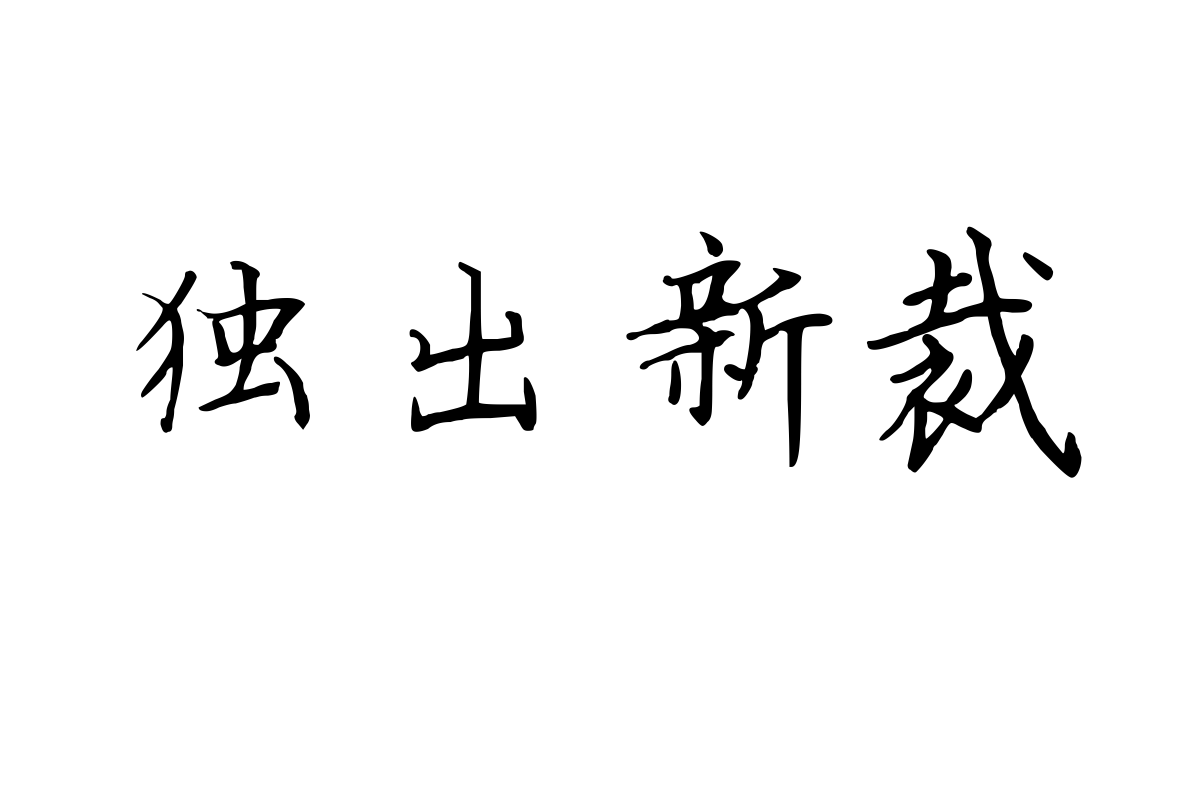
三极青岚楷书字体是一种具有独特美感和艺术价值的书法字体。它由著名书法家李三奇先生设计,融合了传统书法与现代审美,创造出一种既庄重又灵动的字体风格。
三极青岚楷书字体的特点在于其笔画流畅、结构严谨。每个字都经过精心构思,力求在保持原有字形的基础上,增加一些变化和动感。这使得整个字体既有传统书法的韵味,又不失现代感。
此外,三极青岚楷书字体还注重细节的处理。每个字的笔画都有明确的起止点,使得整体看起来更加清晰明了。同时,字体中也融入了一些现代元素,如简化的笔画和装饰性的线条,使得整个字体既有传统韵味,又不失时尚感。
总的来说,三极青岚楷书字体是一种集传统与现代于一体的书法字体,适合用于各种场合的展示和宣传。无论是在商业广告、品牌标识还是个人作品展示中,都能展现出独特的魅力和价值。